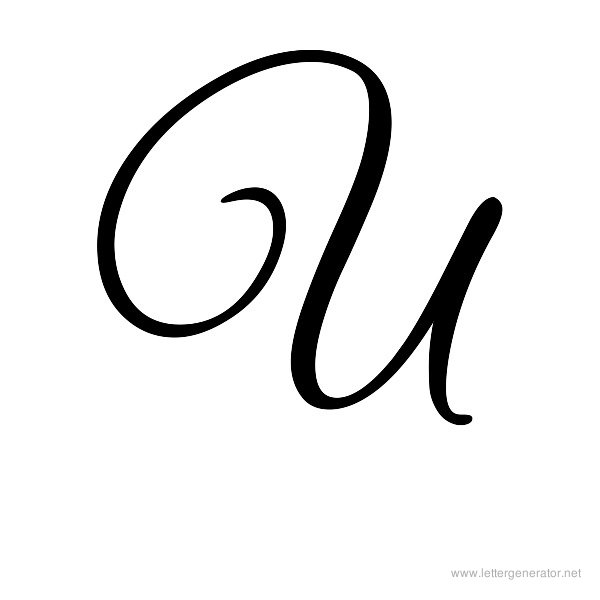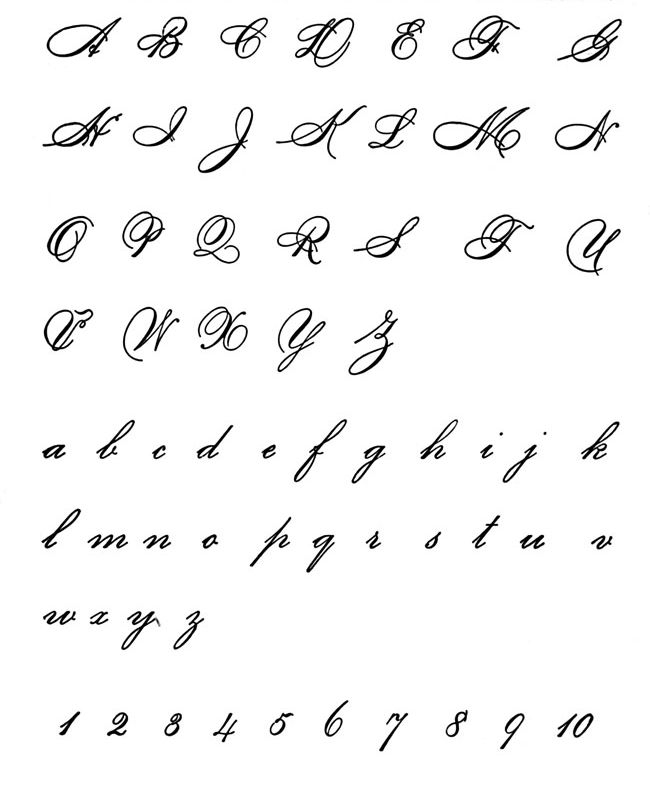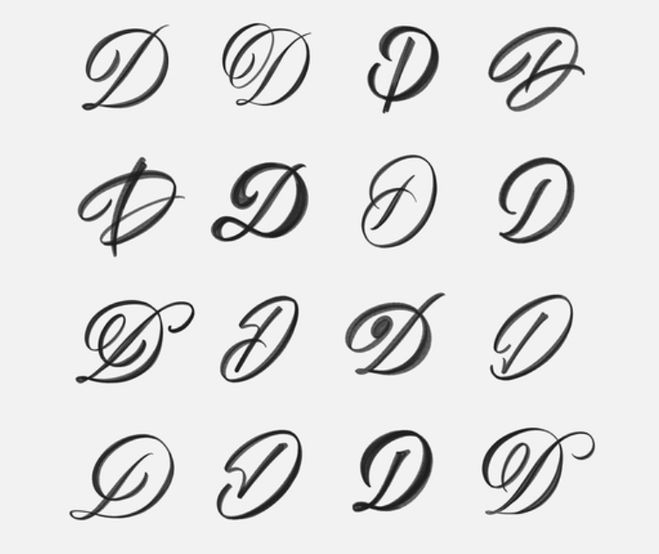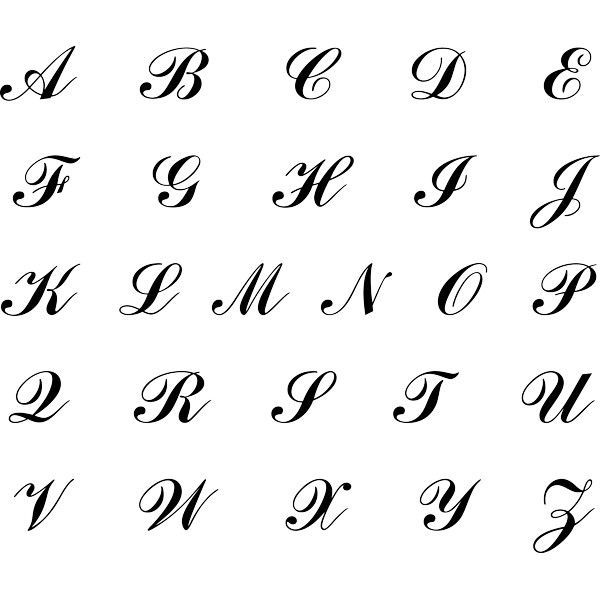
что это за старинное искусство изысканного письма
Пример каллиграфического текста. ИсточникИстория возникновения каллиграфииПервые упоминания об искусстве красивого письма датируются 4000 годом до н.э., а родом оно из Китая. Здесь к каллиграфии относились со всей серьезностью, называя ее «первой среди художеств», а заодно предъявляли высокие требования к мастерам письма. Культура Китая отличается уважительным отношением к изобразительному искусству, вниманием к мельчайшим деталям. Страна является родиной бумаги, поэтому неудивительно, что именно в Китае каллиграфия не только возникла, но и получила распространение и наполнение смыслами.
Но это вовсе не означает, что только Поднебесная обладает монополией на каллиграфию. Этот вид искусства возникал независимо друг от друга почти во всех культурах на протяжении становления цивилизации. Сегодня можно говорить сразу о нескольких ветвях развития каллиграфии.
- Восточноазиатская. К ней относится китайский стиль искусного письма.
В китайские иероглифы закладывались глубокие философские смыслы, а искусство ставилось на один уровень с поэзией, литературой и считалось утонченной формой живописи. Из Китая феномен каллиграфии распространился на соседние страны: Вьетнам, Корею, Японию, Монголию и другие.
- Арабское искусство письма. Связано с зарождением ислама на Ближнем Востоке. При помощи витиеватых букв ученые и богословы копировали священную книгу мусульман — Коран. Ислам запрещает изображение людей и животных, но не регламентирует особенности написания, поэтому арабская вязь стала чуть ли не именем нарицательным.
- Европейская каллиграфия. Берет начало от алфавитов Древних Греции и Рима, которые, в свою очередь, легли в основу всего европейского письма. Затейливыми орнаментами из букв украшали памятники, архитектурные сооружения, писались законы, важные рукописи.
Особого внимания заслуживает византийская ветвь развития каллиграфии: с появлением и распространением христианства письменное исполнение библейских текстов становилось все более вариативным и индивидуальным. Знаменитый готический стиль просуществовал почти 10 столетий, до самой эпохи Возрождения.
Ученые, изучающие древние артефакты и письменность, выделяют также персидскую, индийскую, еврейскую, армянскую каллиграфию. Течения рукописного искусства в разные эпохи имели различные масштабы развития и использовались чаще всего для оформления религиозных текстов.
Современные виды каллиграфииВ современном изобразительном искусстве за последние столетия каллиграфия не только не потеряла свою актуальность, но даже получила широкое распространение в мире цифровых технологий. Изначально каллиграфия относилась к рукописному искусству, то есть выполнялась полностью вручную, буквы и тексты наносились на пергамент, ткань, шелк кистью или пером.
С возникновением книгопечатания каллиграфия перешла в сферу интересов граверов и художников и все чаще использовалась только по особым случаям.
С появлением рекламы и возникновением цифровой среды каллиграфия обрела второе дыхание. Можно говорить о двух направлениях развития древнего искусства.
- Ручное изображение. Штучный товар, дорогой и уникальный. Это могут быть объекты украшения интерьера, ручное оформление обложек уникальных книг, персонализированные подарки. Часто встречается в оформлении городской среды, арт-объектах. Буквы и символы наносятся на поверхности различных объектов, холст, ткани.
- Цифровое изображение. Получило распространение с развитием рекламы и брендинга. Используется как элемент фирменного стиля, в оформлении книг, визиток, печатной продукции и др.
Она распространилась во многие сферы творческой жизни и дизайна.
Искусство. Яркий пример современного каллиграфа — художник Покрас Лампас.
Покрас Лампас и его каллиграфическая работа Enter The Void. ИсточникБрендинг. Дизайнер использует каллиграфию в буквенных логотипах и элементах фирменного стиля, упаковки.
Логотип для бренда украшений от Dzina Zhadanova. ИсточникДизайн полиграфии. Уникальные, специально разработанные шрифты часто используются как элементы пригласительных, открыток, афиш, буклетов.
Оформление приглашения на мероприятие от Lina Romanova. ИсточникИндустрия татуировок. С развитием тату-арта надписи, выполненные затейливыми буквами, встречаются в любой точке мира на самых неожиданных частях тела.
Эскиз татуировки, выполненной каллиграфией. ИсточникХобби. Каллиграфия популярна в качестве досуга не только в Азии, где зародилась, но и в западном мире. Причин этому множество: от успокаивающего, медитативного воздействия на нервную систему до развития умственных навыков через технику мелкой моторики, а также улучшение внимания, концентрации.
Это далеко не все возможные сферы применения каллиграфии. Искусно написанные буквы используются во всех областях дизайна.
Каллиграфия, леттеринг, типографика — в чем отличия?Не стоит путать каллиграфию и леттеринг. Леттеринг имеет отношение к дизайну и считается искусством рисования, а не написания букв, в отличие от каллиграфии. В леттеринге буква или слово являются иллюстрацией объекта или послания, которое зашифровал художник. Этот стиль изобразительного искусства часто можно встретить в брендинге, граффити или, например, комиксах.
советов, как правильно писать красиво
Одна полезная мнемоника для запоминания того, как пишется красивое , — использовать фразу «Будь «полезным» человеком!» Таким образом, вы можете не забыть начать с B-E-A , а затем все, что вам нужно сделать, это добавить выдуманное слово utiful в конце.
В китайские иероглифы закладывались глубокие философские смыслы, а искусство ставилось на один уровень с поэзией, литературой и считалось утонченной формой живописи. Из Китая феномен каллиграфии распространился на соседние страны: Вьетнам, Корею, Японию, Монголию и другие.